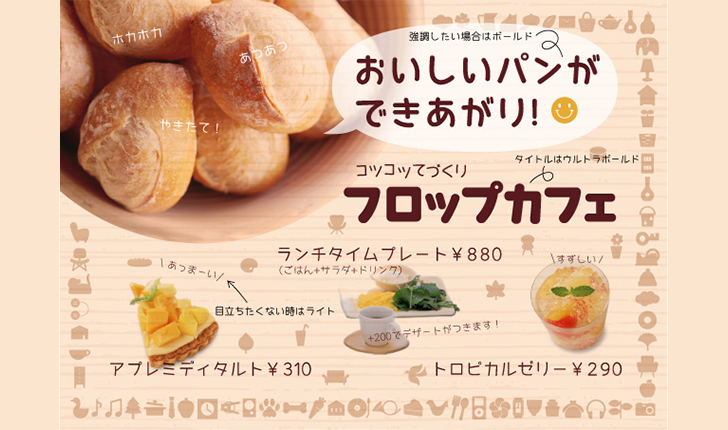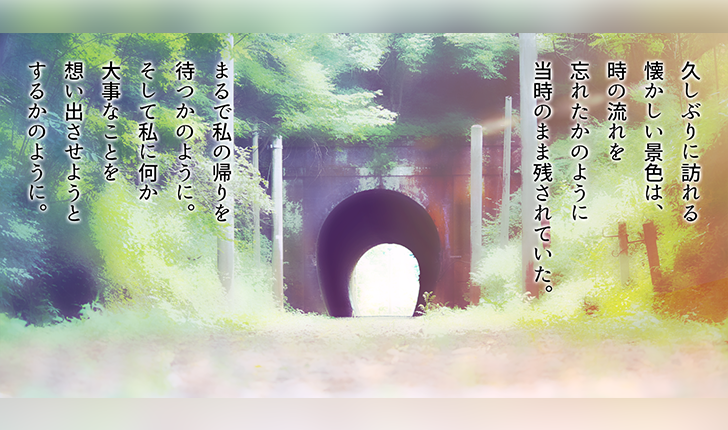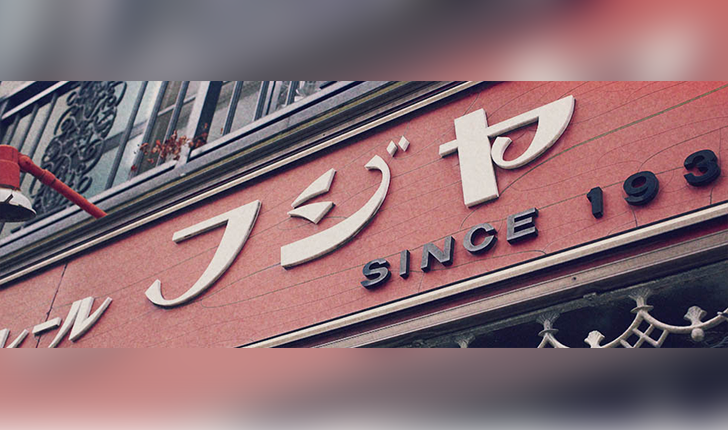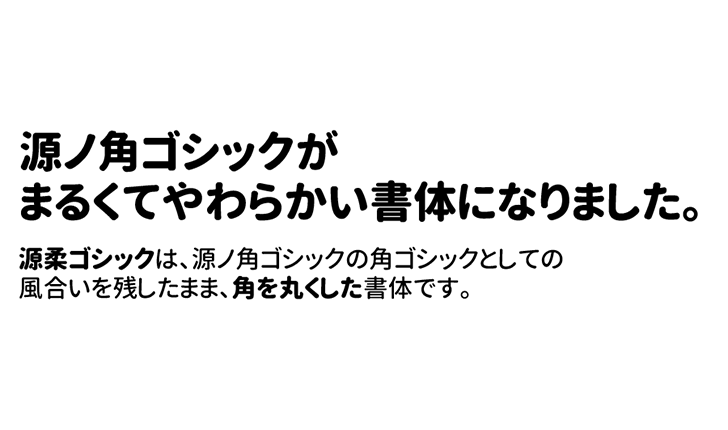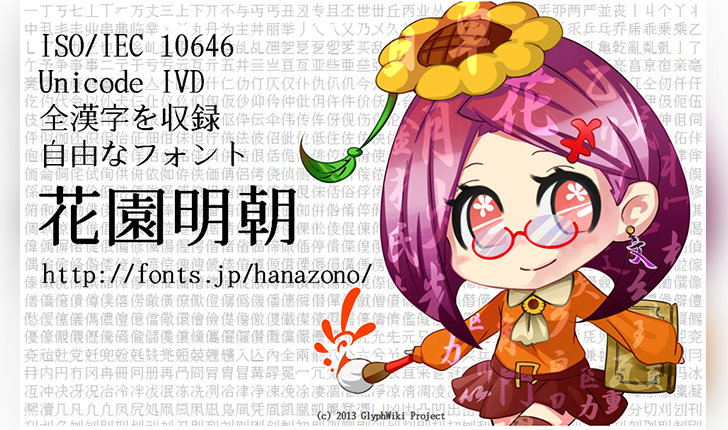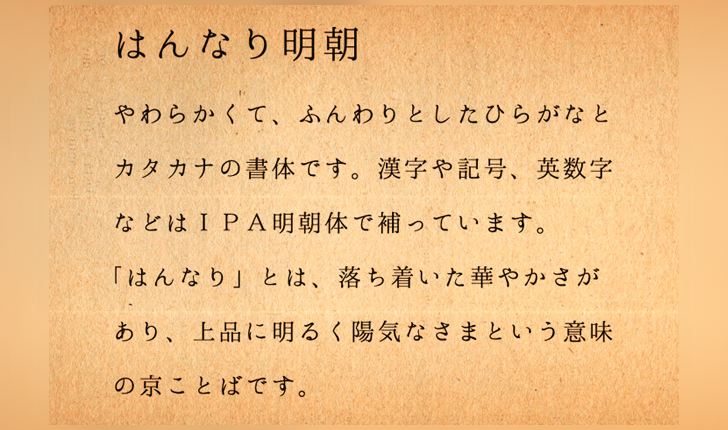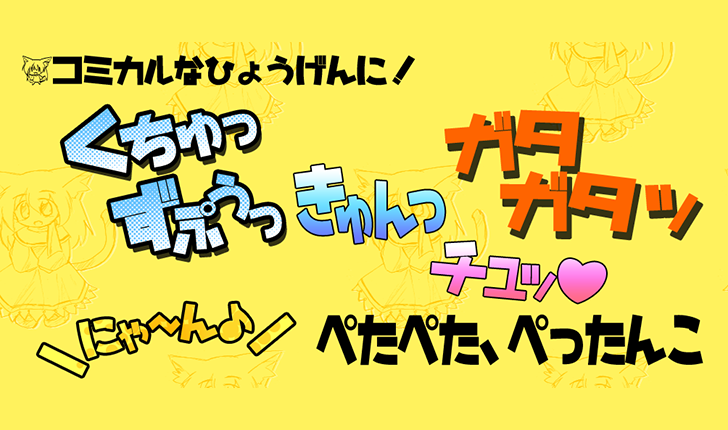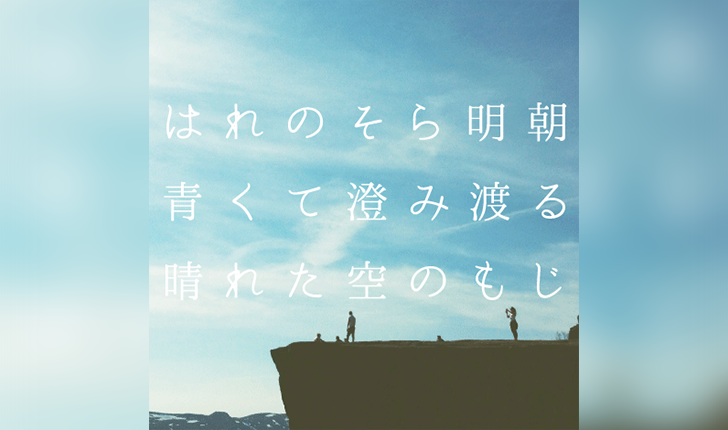
同人誌に使えるフリーフォント、21個を紹介します。
漫画でよく使われる、ゴシック体の漢字に太めの明朝体のかなを組み合わせたアンチゴシック体、通称、アンチゴチのフォントや、楽しい雰囲気を演出できるポップ体のフォント、小説などに使いやすい明朝体のフォント、魔法陣や呪文っぽいフォントまで、同人誌でよく見かけるフォントを厳選しました。
新コミック体
新コミック体は、アンチック書体の漫画セリフ用フォントです。フォントサイズが小さくても読みやすい仕上がりで、漫画のセリフ内での使用におすすめです。文字にクセが無く、バランスのいいフォントです。無料でダウンロードできて、商用、同人誌での利用が可能です。
新コミック体
やさしさアンチック
やさしさアンチックは、漫画などで使われるアンチック書体のフォントです。アンチック書体は、アンチゴチとも呼ばれ、ゴシック体の漢字に、太めの明朝体のかなを組み合わせたフォントで、漫画などで一般的に使われています。無料でダウンロードできて、同人誌やコミックでも使うことができます。
やさしさアンチック
源柔ゴシック
源柔ゴシックは、柔らかい印象の角丸の日本語フォントです。丸みの度合いによりひかえめ、標準、太めの3つのバリエーションがあります。さらに、文字の太さは7種類、プロポーショナル、等幅の書体も用意されています。同人漫画などの回想シーンや心の声を表現する際に活用できます。無料ダウンロードできて、商用、同人誌での利用も可能です。
源柔ゴシック
りいポップ角
りいポップ角は、女の子っぽい、ポップ体の、手書きフォントです。楽しい雰囲気を演出したいときに使えます。年齢制限のある創作物でも利用可能です。
りいポップ角
源真ゴシック
源真ゴシックは、AdoseとGoogleが共同開発したフォント「源ノ角ゴシック」をベースとして作成されたフォントです。OpenTypeの「源ノ角ゴシック」を、TrueTypeに変換し、各種調整が行われています。縦書きでも使うことができます。無料ダウンロードできて、商用、同人誌での利用も可能です。
源真ゴシック
g_コミックホラー(教漢版)
g_コミックホラー(教漢版)は、ホラーな雰囲気を演出したいときに使える、ガタガタと震えたような字体のフォントです。細字のかすれ具合が恐怖を演出します。無料でダウンロードできて、商用、同人誌での利用が可能です。
g_コミックホラー(教漢版)
しょうわのにをい
しょうわのにをいは、昭和レトロな雰囲気のあるフォントです。昭和をイメージしたお菓子のパッケージや看板のデザインなどに活用できます。ひらがなのみのフォントです。
しょうわのにをい
Kazesawa フォント
Kazesawa フォントは、画面での見やすさと、情報密度の両立を目指した日本語フォントです。ウェイトは、Extralight、Light、Regular、Semibold、Bold、そして、Extraboldと6種類が用意されています。スライドやウェブブラウザでの使用におすすめです。自由なライセンスで、無料で利用できます。Webフォントとしての使用も可能です。
Kazesawa フォント
うつくし明朝体
うつくし明朝体は、横書きでも美しく使うことができる明朝体フォントです。縦書きに向いているオールドスタイルの明朝体の良さを残しつつ、モダンな横書きでも使える明朝体フォントとして仕上げてあります。漢字は第二水準まで収録されています。無料でダウンロードできて、商用利用可能です。
うつくし明朝体
こころ明朝体
こころ明朝体は、少しほっそりとしたスタイルが特徴的な、角丸の明朝体フォントです。晴れやかで、うきうきとしたような、まろやかで軽い漢字のフォントです。無料でダウンロードできて、商用利用可能です。
こころ明朝体
はんなり明朝
はんなり明朝は、築地体を参考にした日本語フォントです。やさしくて、ふんわりとしたひらがなとカタカナが特徴です。
はんなり明朝
はれのそら明朝
はれのそら明朝は、晴れた空のように、澄み切った、清々しい印象のフォントです。美しい曲線と、シャープなハネのリズム感のいい仕上がりです。無料でダウンロードできて、商用利用可能です。
はれのそら明朝
花園フォント
花園フォントは、収録文字数が97,745字と大変豊富なフォントです。日常で使用する漢字から、通常のフォントには収録されていないような漢字まで、様々な漢字を使用することができます。無料でダウンロードできて、商用利用可能です。
花園フォント
あいこフォント
あいこフォントは、20歳くらいの女性の手書き文字を参考にして作成された、手描き風フォントです。最近の女性の文字のクセを取り入れた、モダンなフォントです。学園祭、同人誌、個人ブログ、個人HP、学生の学校、ニコニコ、クラブフライヤーでの使用は無料です。商用利用は有料です。
あいこフォント
はらませにゃんこ
はらませにゃんこは、コミカルな表現に最適な、太字のフォントです。縁取りや影をつけて使うのに最適です。無料でダウンロードできて、商用利用可能です。
はらませにゃんこ
フジヤ
フジヤは、1932年に創業したパン屋さん「フジヤ」の本物の看板文字をベースに作成されたフォントです。時代を経た味わいあるフォントが楽しめます。カタカナのみの収録です。寄付での有料ダウンロードか、ツイッターやFacebookでシェアをする無料ダウンロードか選ぶことができます。どちらの場合も、商用利用可能です。
フジヤ
セプテンバー
セプテンバーは、漫画で使われるファニーという書体に似たフォントです。手描き風の愛らしい字体が特徴です。有料フォントです。
セプテンバー
ロゴたいぷゴシック
ロゴたいぷゴシックは、かっこよさとエレガントさを兼ね備えたポップなフォントです。ロゴやタイトルでの使用に向いています。漢字は第二水準文字の一部まで収録されています。無料でダウンロードできて、商用利用可能です。
ロゴたいぷゴシック
刻明朝フォント
刻明朝フォントは、通常サイズの漢字に、小さなひらがなとカタカナを組み合わせたフォントです。人工的で機械的な「硬さ」が特徴です。無料ダウンロードできて、商用利用可能です。
刻明朝フォント
魔法陣文用フォント
魔法陣文用フォントは、魔法陣を描くときに使える、文字を図形化したフォントです。文字に意味は無いけど、それっぽい感じで並べて使いたいというときに活用できます。無料ダウンロードできて、商用利用可能です。
魔法陣文用フォント